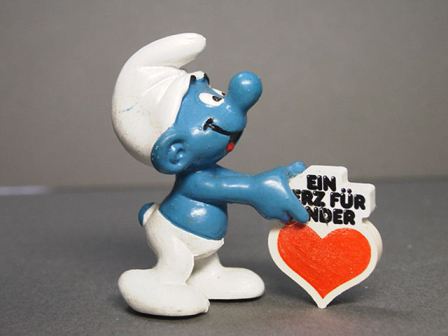
„Ein Herz für Kinder“
sieht aus wie eine elektronisch gefettete »Helvetica rounded«
Frankfurter ist es nicht. Schau dir mal das K und das R an. Von den Buchstabenformen kommts schon eher an die Helv. Rounded ran. Die Bold auf 80% gestaucht kommt hin.
Die hier abgebildete ist es sicher nicht. Ich bin mir nur relativ sicher, daß sie früher zum gleichen Zweck benutzt wurde.
Genau, hier sieht man's noch:
... dein Schlumpf ist frankfurtmäßig überzeugend. Wo hast du denn den ausgegraben?
Ah! Bedankt. Die Lichtreflexe hat der Herr Fleckhaus wohl rausgenommen – also die Frankfurter ist ganz sicher die Basis.